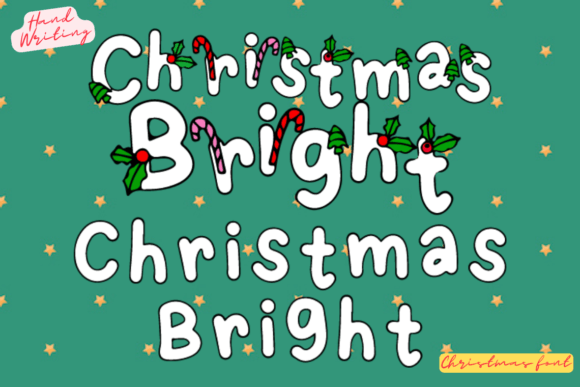
Christmas Font, Crafting Font
Christmas Font, Crafting Font gibi yüksek kaliteli varlıklar arıyorsanız, bu premium paket yaratıcı projeleriniz için harika bir seçimdir.
İster İsteğe Bağlı Baskı (POD) ürünleri, ister düğün davetiyeleri veya sosyal medya grafikleri oluşturuyor olun, Christmas Font, Crafting Font ideal bir uyumdur.